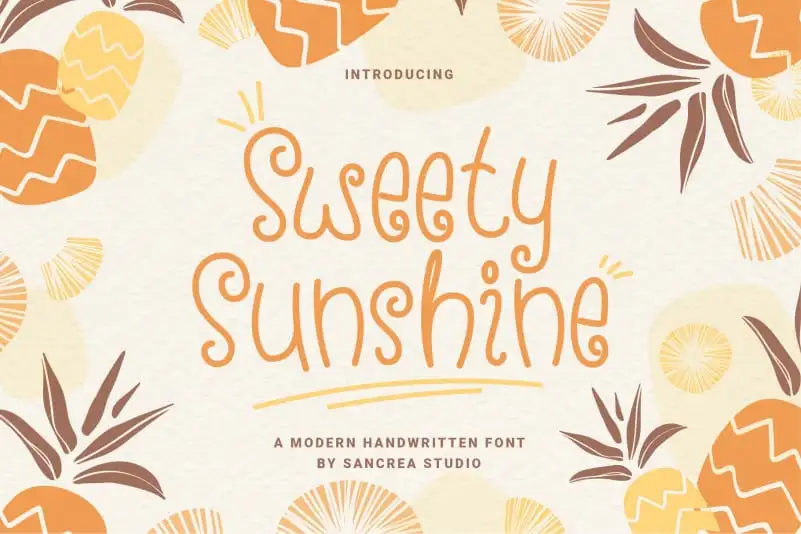
A fonte ‘Sweety Sunshine Display Font’ é uma opção ideal para qualquer projeto que exige uma pitada de descontração durante as férias. Desenvolvida pelo designer 607469, esta fonte traz um toque encantador e criativo para o seu design. Se você está procurando por algo que ilumine seu trabalho com cores alegres e uma atmosfera festiva, ‘Sweety Sunshine Display Font’ é perfeito para isso. Suas formas redondas e traços levemente arranha-pés dão ao texto um ar divertido que vai desde os cartões de aniversário até as embalagens de Natal. Seja você quem está criando, ou quem está recebendo a sua criação, ‘Sweety Sunshine Display Font’ é uma fonte que torna qualquer projeto brilhar, sem deixar de ser amigável e acessível.